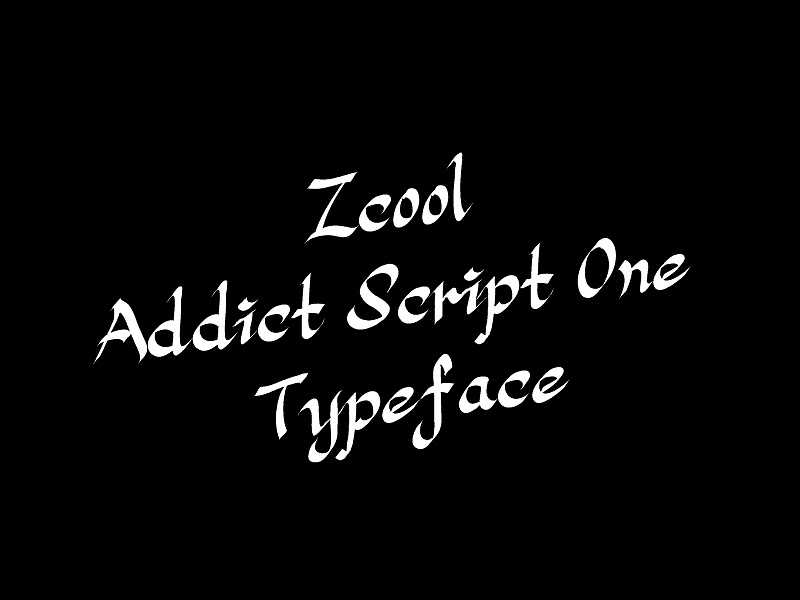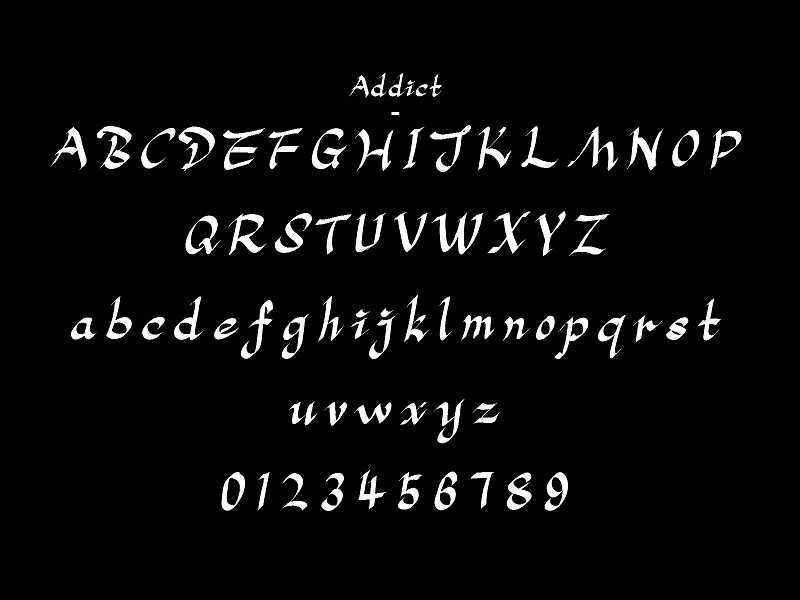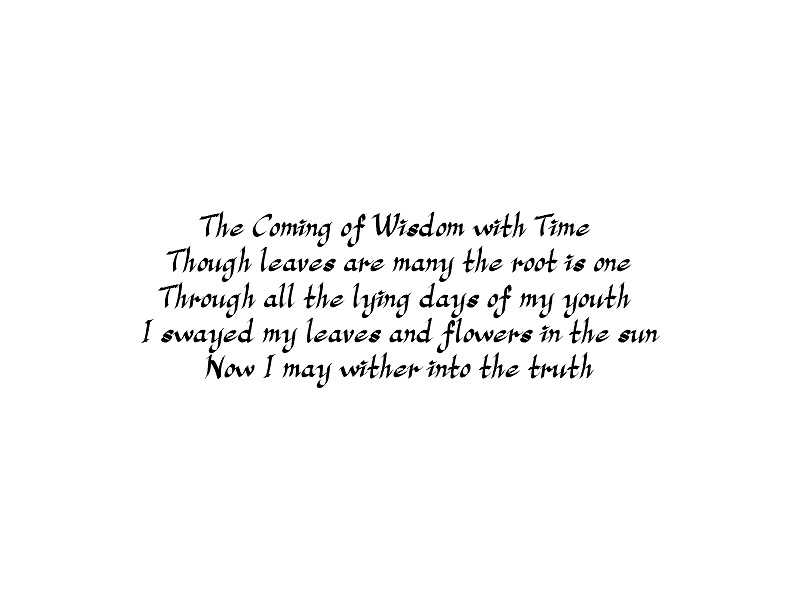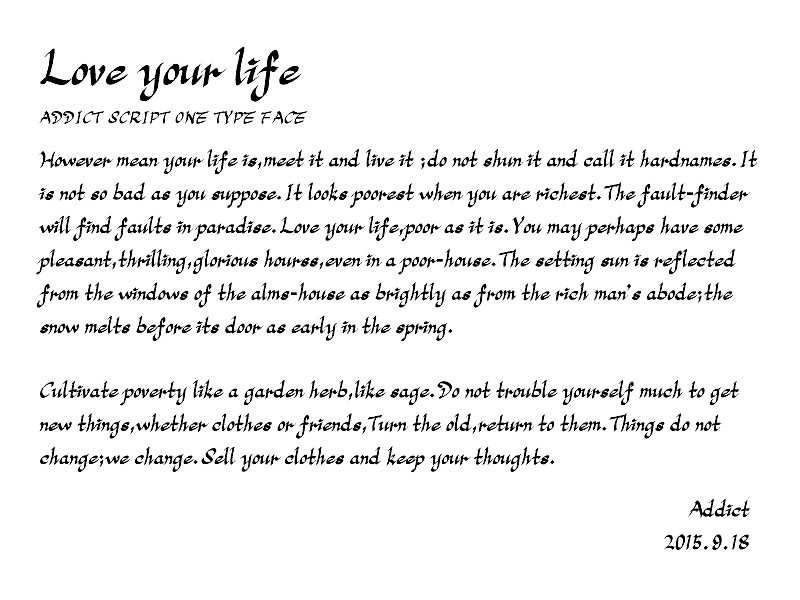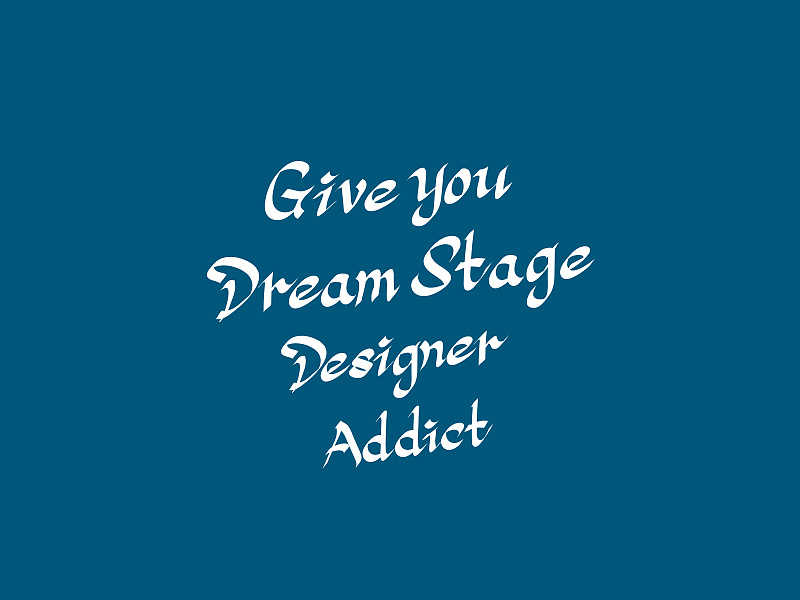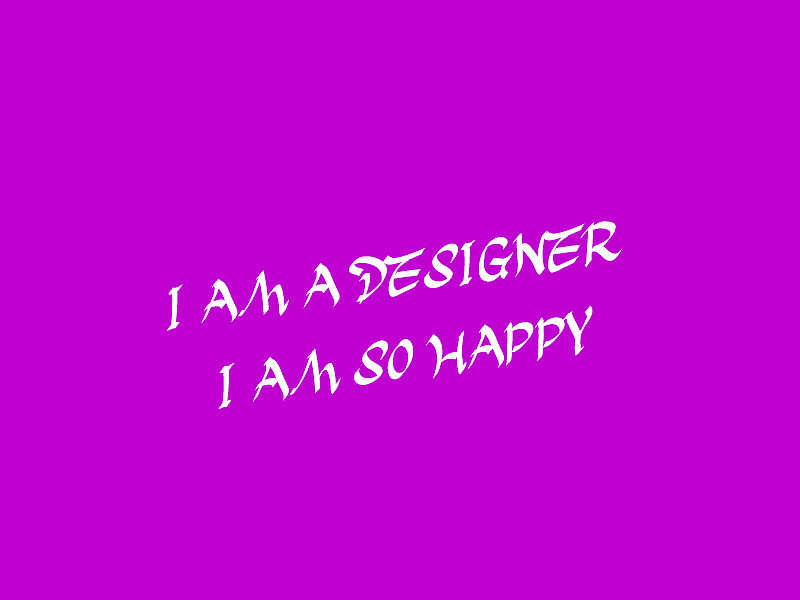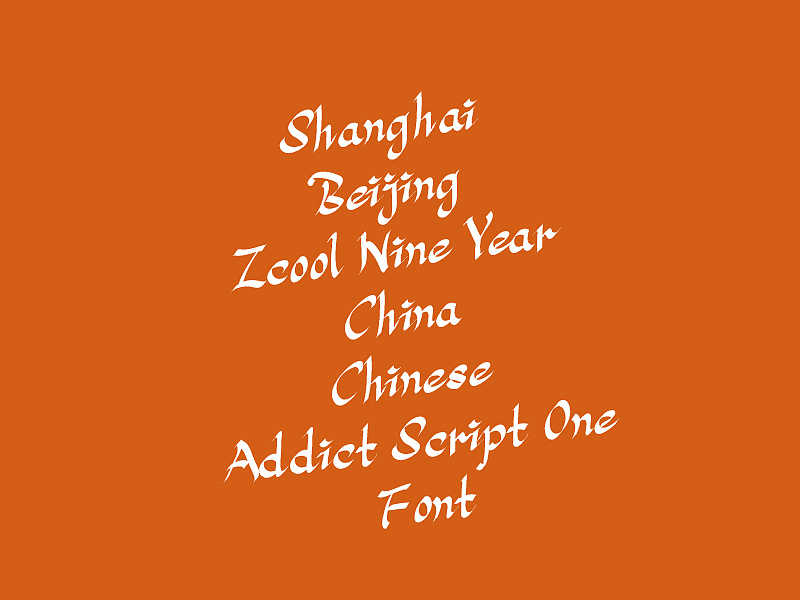
前段时间进行了一套英文字库的开发,直到今天上午才整理出来。
这套字库是手写体的风格,但是加入了oldstyle罗马正体的衬线元素,颇具一番风味
这套字库除了字母和数字外还包括常用的标点和符号,能够广泛用于正文字体和海报等地方
Addict Script One看似随意,实际上也遵循了罗马正体的规则,有标准的升部线、大写线和降部线,只是字形随意洒脱,有另类风味
“Addict Script One”是一款书写很新颖的字体,字体大方,适合各种设计作品使用!欢迎下载!